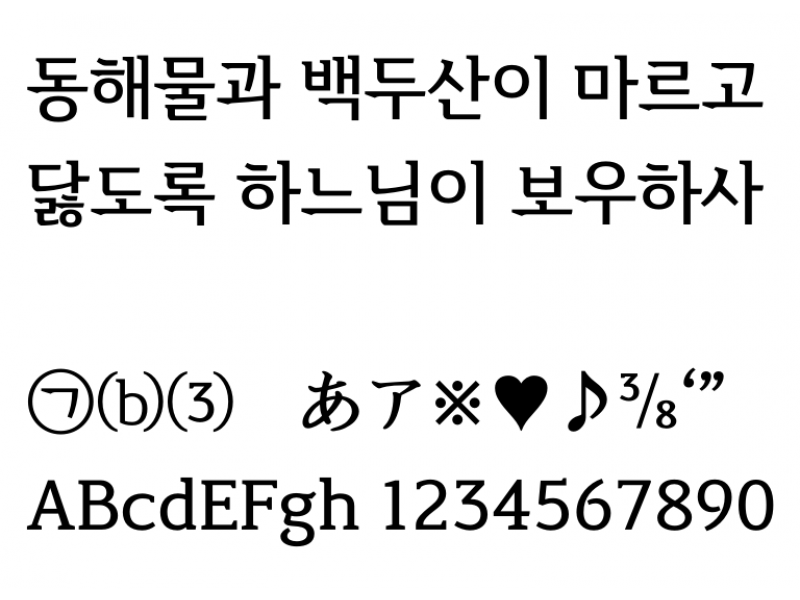
대한체는 한글 문화발전의 일환으로써 윤디자인연구소에서 온국민이 함께 쓸 수 있는 국민을 위한 친근하고 희망적인 메세지를 담아 개발되었다. 대한체는 신뢰성, 친화성, 깨끗함을 상징하며 가독성이 뛰어나 누구나 쉽게 읽고 쓸 수 있다. 글꼴 변형은 불가하며 임베딩할 경우 별도 허가가 필요하다.